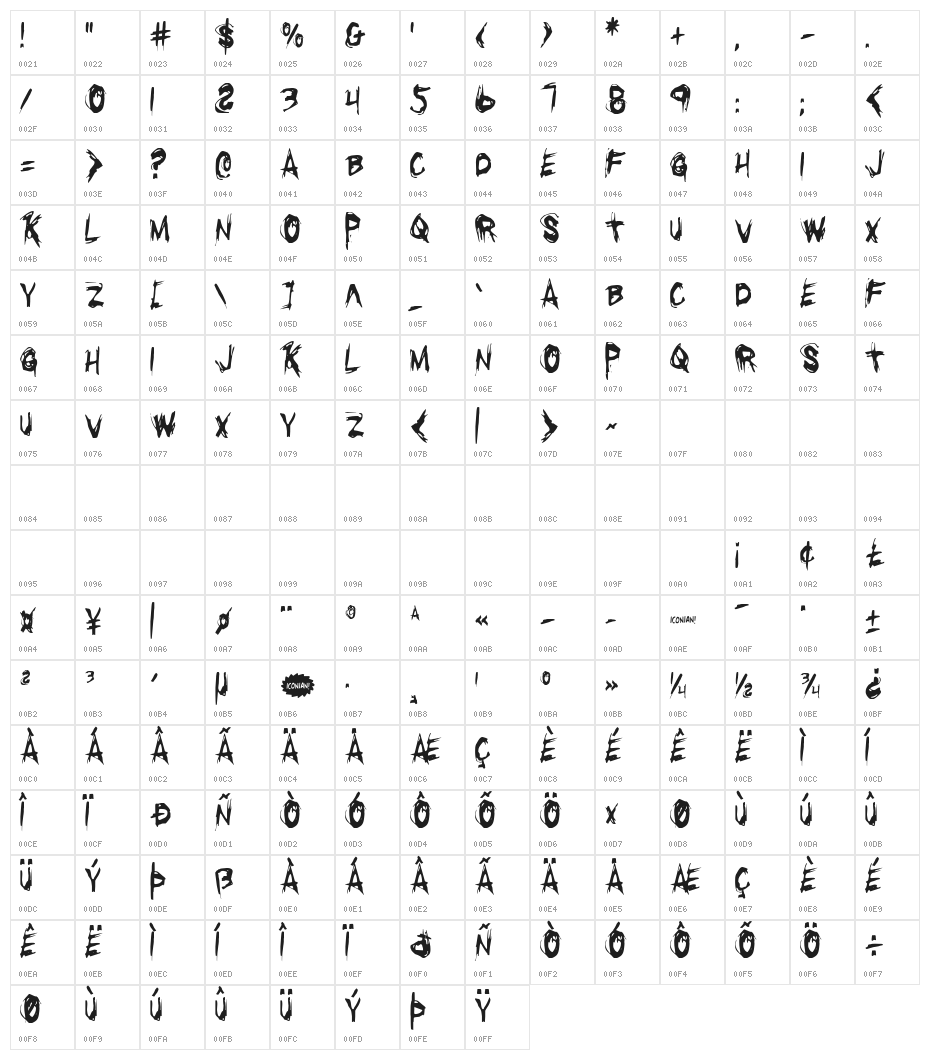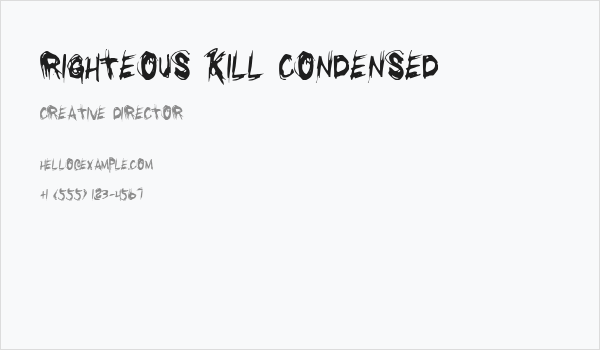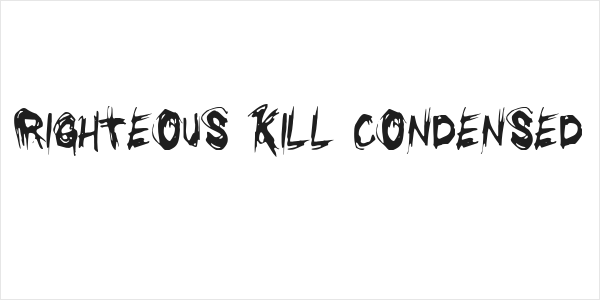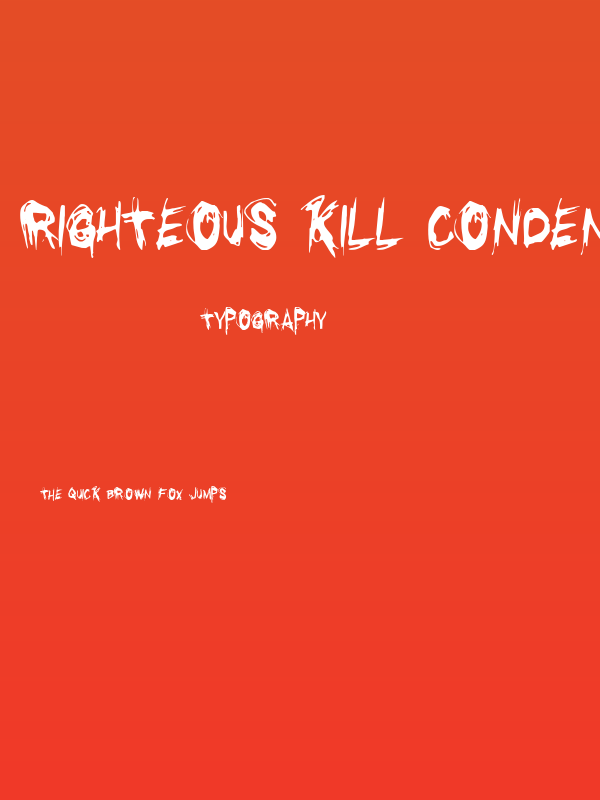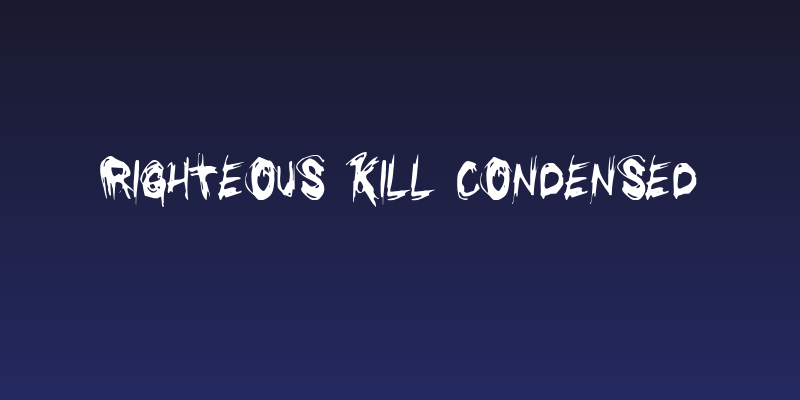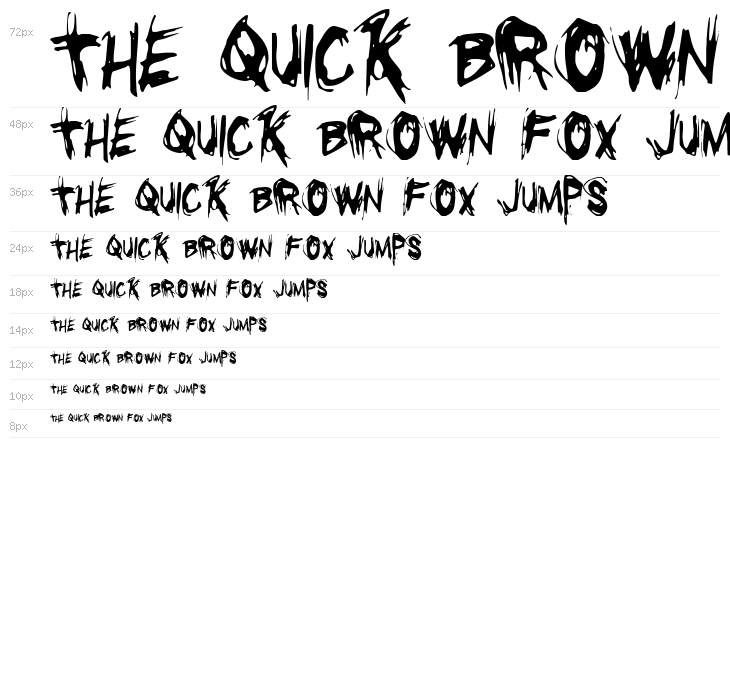
Righteous Kill Condensed Font
✎ Thick
| नाम | Righteous Kill Condensed |
| वजन | Condensed |
| श्रेणियाँ | Thick |
| चौड़ाई | Condensed |
| कंट्रास्ट | High |
| समग्र शैली | Decorative |
| उपयोग का मामला | Headlines, Posters, Branding |
| सुझाए गए प्रोजेक्ट | Ideal for horror movie posters, Halloween event flyers, edgy album covers, and rebellious fashion branding. |